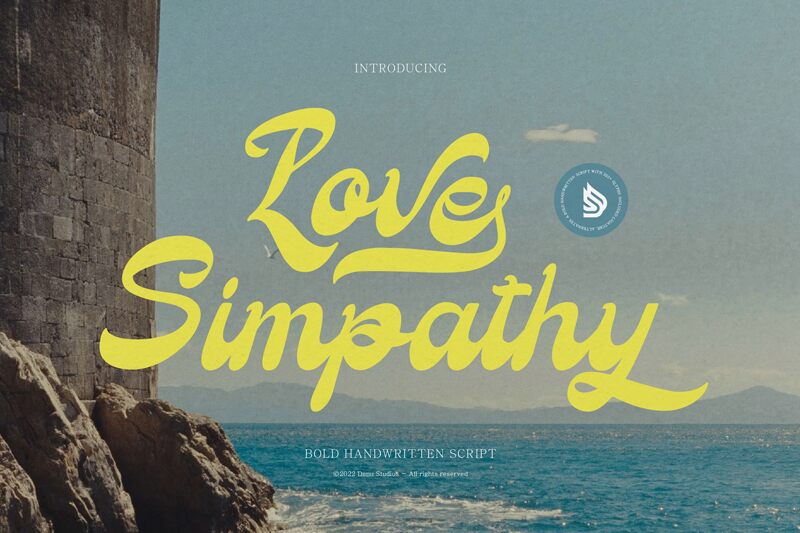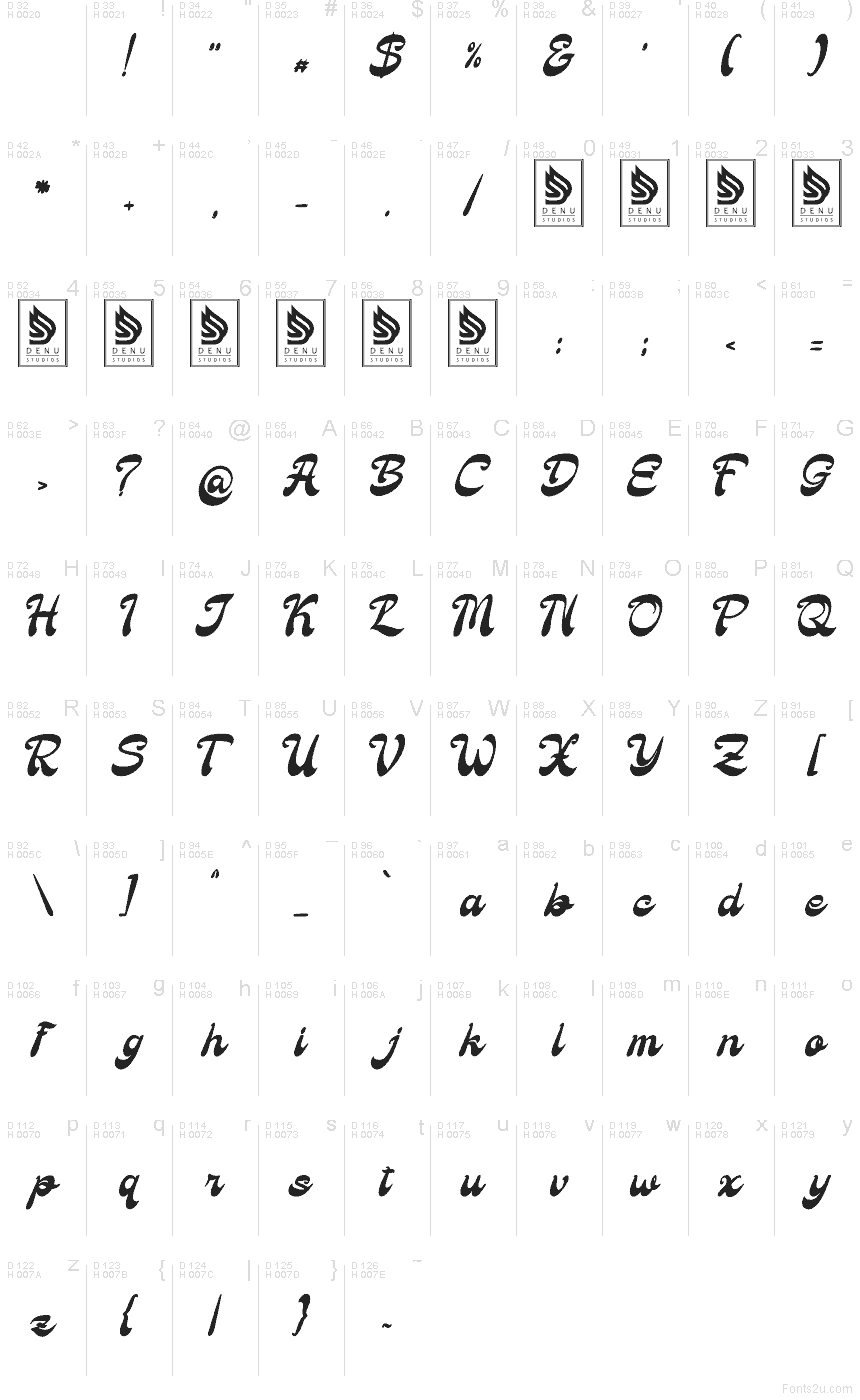
Love Simpathy de Denustudios es una tipografía script tipo pincel gratuita con un estilo romántico y un trazo hecho a mano. Sus letras se inclinan hacia trazos largos y ondulados y formas rellenas conectadas, dando a la fuente un ritmo suave y cariñoso que se siente más como una dedicatoria rápida hecha a mano que como una caligrafía formal.
Encaja a la perfección en papelería de bodas, branding de belleza, etiquetas de velas, packaging boutique y tarjetas de citas para redes sociales, donde esos remates en bucle permiten que una frase corta destaque por sí sola. Al ser una fuente gratuita, también es ideal para portadas, tarjetas de título y monogramas cuando buscas un estilo cálido y personal sin que resulte rígido.